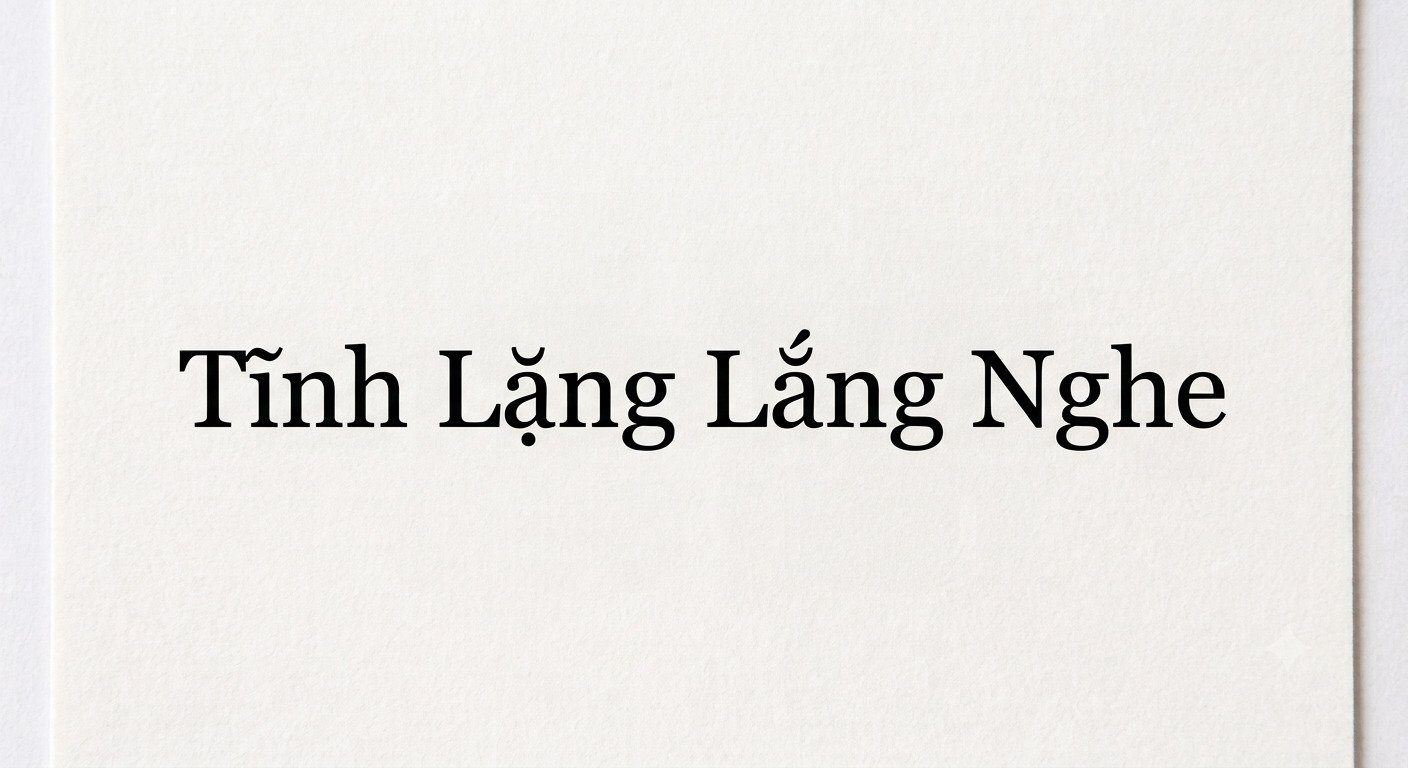
Với phong cách chữ serif cổ điển nhưng vẫn giữ được sự thanh lịch, Georgia Font là lựa chọn phổ biến trong nhiều thiết kế thương hiệu, bao bì và ấn phẩm cao cấp. Tuy nhiên, không phải phiên bản font nào cũng hỗ trợ tiếng Việt hoàn chỉnh, gây khó khăn khi chỉnh sửa và in ấn thực tế.
Georgia font là gì?
Georgia font là một bộ phông chữ thuộc dòng Serif (chữ có chân) kinh điển, được thiết kế bởi Matthew Carter cho tập đoàn Microsoft vào năm 1993. Ban đầu, Georgia được tối ưu hóa để hiển thị rõ nét trên màn hình máy tính có độ phân giải thấp, nhưng nhờ vẻ đẹp trang nhã và thanh lịch, nó đã trở thành “ông vua” trong cả lĩnh vực in ấn truyền thống. Đặc trưng của Georgia là chiều cao ký tự (x-height) lớn và các đường chân chữ vững chãi, tạo cảm giác tin cậy, uy tín và vô cùng dễ đọc.
Trong giới đồ họa chuyên nghiệp, phiên bản Svn georgia pro thường được ưu tiên sử dụng cho các dự án nhận diện thương hiệu tầm cỡ tập đoàn. So với bản tiêu chuẩn, bản Pro cung cấp nhiều biến thể về độ dày và các ký tự thay thế nghệ thuật hơn. Bản font georgia việt hóa được Xưởng In Viva chia sẻ đã được tinh chỉnh kerning hoàn hảo cho ngôn ngữ tiếng Việt, đảm bảo các dấu mũ, dấu thanh không bị chồng chéo, mang lại sự cân đối tuyệt đối cho các đoạn văn bản dài trên Catalogue hay Brochure doanh nghiệp.
Lưu ý: Georgia có thiết kế số (Numbers) theo phong cách “Old-style” (các con số có độ cao không bằng nhau). Đây là nét đặc thù mang tính nghệ thuật cao, tuy nhiên khi in bảng giá sản phẩm, bạn nên kiểm tra kỹ để đảm bảo khách hàng không bị nhầm lẫn.
5 ứng dụng font Georgia việt hóa trong thiết kế và in ấn
Vẻ đẹp bền vững và uy tín của Georgia giúp nó trở thành trợ thủ đắc lực trong nhiều ngành hàng đòi hỏi sự chuyên nghiệp cao:
- Thiết kế hồ sơ năng lực (Company Profile): Georgia giúp các đoạn văn bản dài trở nên thoáng đạt, dễ đọc, tạo dựng niềm tin vững chắc về sự chỉn chu của doanh nghiệp đối với nhà đầu tư.
- Sản xuất bao bì dược phẩm và thực phẩm chức năng: Sự rõ nét và vững chãi của font chữ này gợi nhắc về tính chính xác và an toàn, rất phù hợp để in thông tin thành phần trên hộp giấy cao cấp.
- In ấn quà tặng tri ân đối tác VIP: Logo dùng font SVN Georgia Pro in nung trên bộ ấm chén gốm sứ hoặc khắc laser trên hộp trà gỗ tạo vẻ ngoài đẳng cấp quốc tế.
- Thiết kế bao bì ngành rượu và yến sào: Kết hợp Georgia cùng kỹ thuật in ép kim nhũ đồng trên nền hộp cứng tối màu mang lại hiệu ứng thị giác sang trọng bậc nhất.
- Trang trí voucher và thiệp mời sự kiện trang trọng: Những dòng tiêu đề sử dụng Georgia mang lại cảm giác truyền thống, quý tộc cho các buổi tiệc khánh thành hoặc kỷ niệm thành lập tập đoàn.
5 lưu ý khi sử dụng font chữ Georgia
Để bản in sử dụng font Georgia đạt độ thẩm mỹ cao nhất trên mọi chất liệu, designer cần chú trọng các điểm sau:
- Lựa chọn cỡ chữ phù hợp: Georgia có các nét Serif nhỏ và tinh tế, vì vậy khi in trên giấy Ivory hoặc giấy mỹ thuật nên sử dụng cỡ chữ từ 8pt trở lên để hạn chế tình trạng mất nét khi thấm mực.
- Tối ưu đường Path khi gia công bế nổi: Chuyển đổi font Georgia sang dạng vector giúp các chi tiết chữ được giữ chính xác khi gia công. Đặc biệt với logo hoặc tên thương hiệu trên hộp quà, kỹ thuật này giúp đường nét nổi rõ và hạn chế bong rách bề mặt giấy.
- Kiểm soát màu CMYK khi in: Georgia phù hợp với các gam màu sang trọng như đen, xanh Navy, đỏ đô hoặc nâu trầm. Thiết lập đúng hệ màu CMYK giúp chữ sau in giữ được độ sâu và sự cao cấp.
- Kết hợp cùng font không chân: Nên sử dụng Georgia cho tiêu đề, logo hoặc thông điệp chính và kết hợp font Sans-serif cho phần nội dung phụ để tạo bố cục cân bằng, dễ đọc.
- Điều chỉnh khi in trên vải: Với các sản phẩm như túi vải canvas, nét Serif mảnh của Georgia có thể bị giảm độ rõ khi in. Nên tăng nhẹ độ dày nét hoặc kích thước chữ để đảm bảo hình ảnh sau in sắc nét hơn.